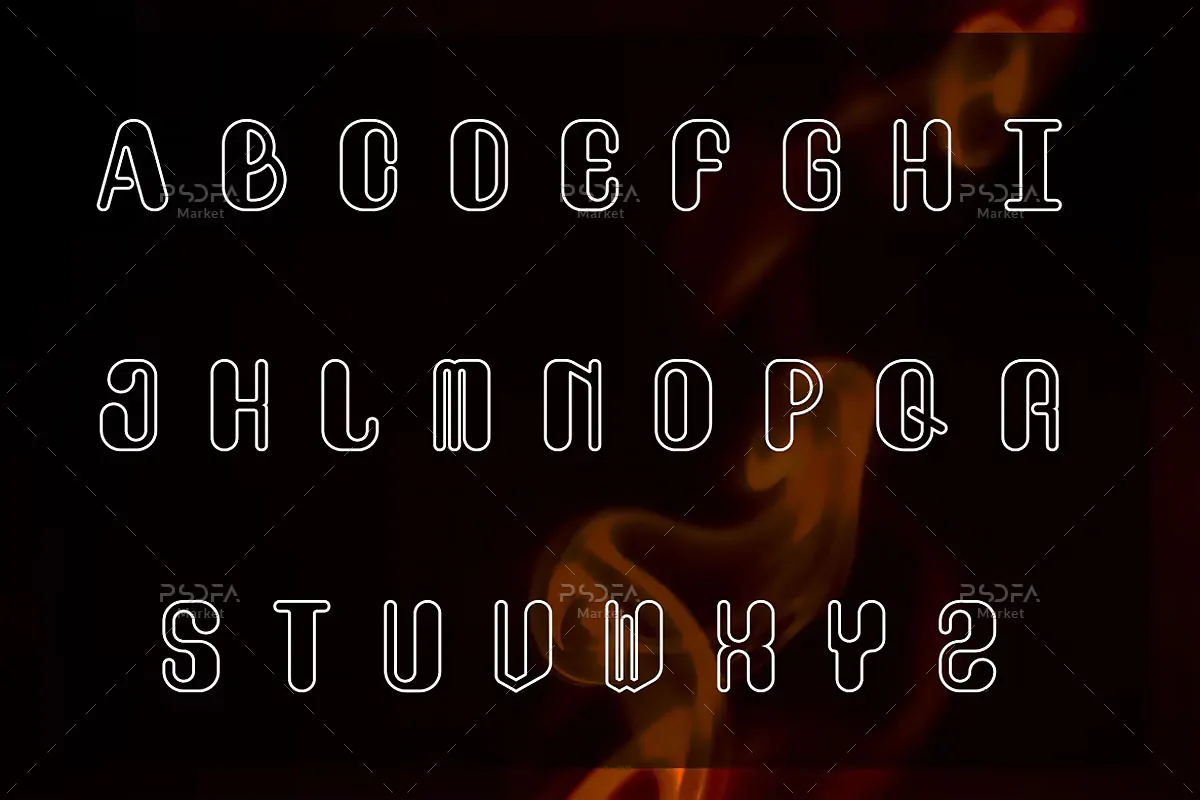
فونت توخالی گوشه گرد Nepita Line
فونت توخالی گوشه گرد
فونت توخالی گوشه گرد Nepita Line یک قلم نمایشی فوق العاده زیبای انگلیسی است که مناسب جهت استفاده در طرحهای گرافیکی مختلف به خصوص طراحی لوگو میباشد. فونت Nepita Line با وزن معمولی طراحی شده است که میتوانید از آن در طراحی پوستر، لوگو، برندینگ، کارت ویزیت، بسته بندی محصولات، ظروف یکبار مصرف، لوازم التحریر و … استفاده کنید.